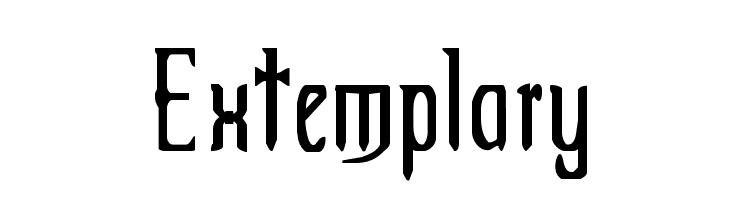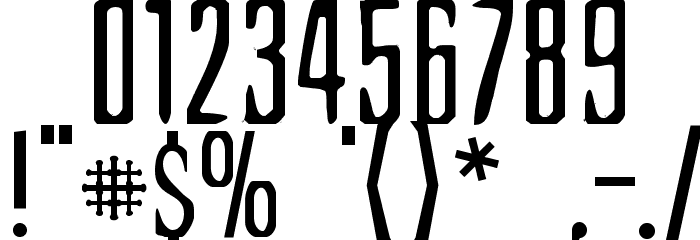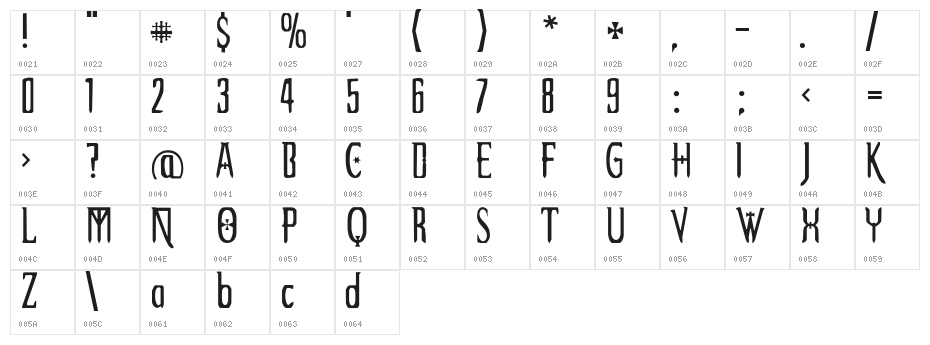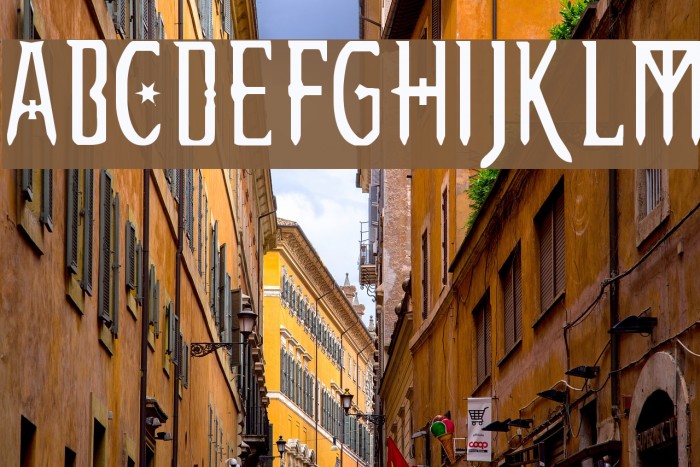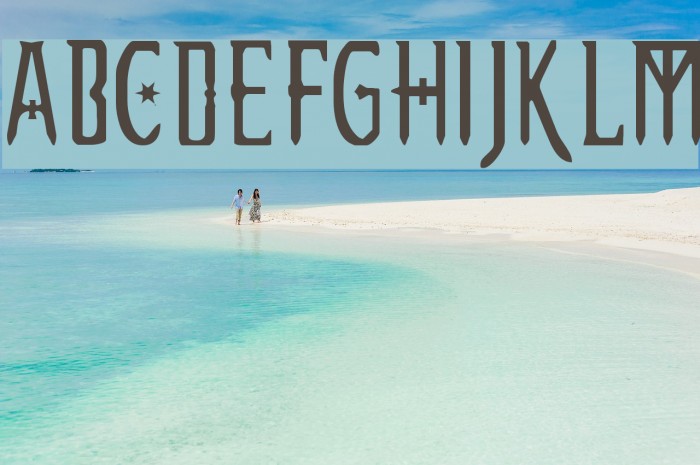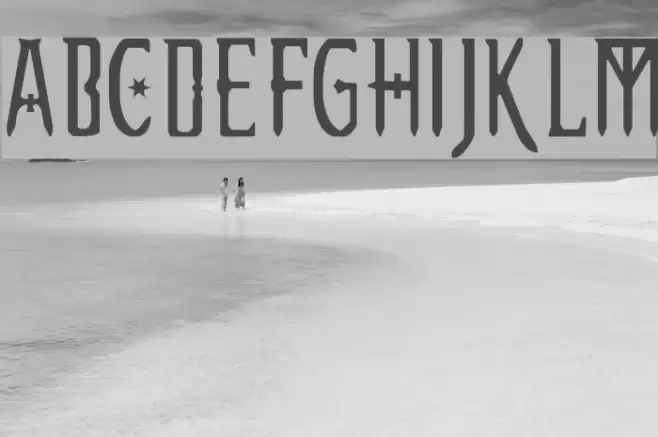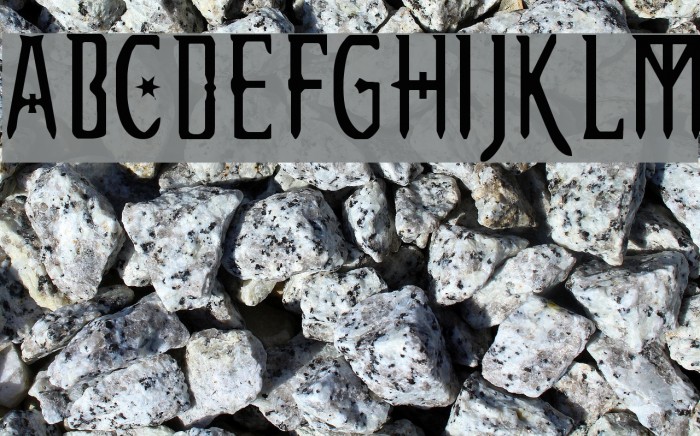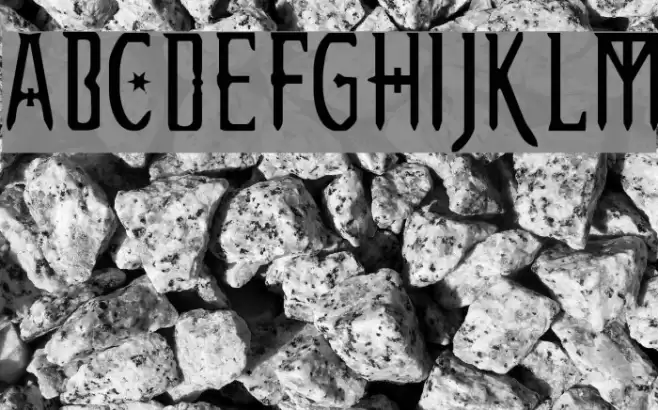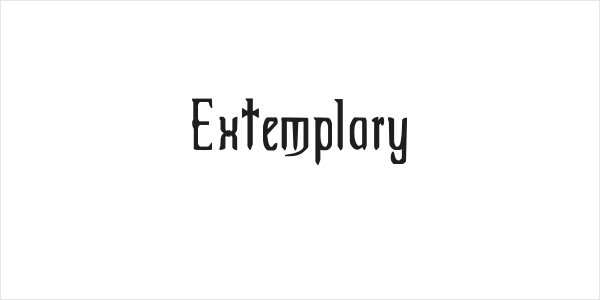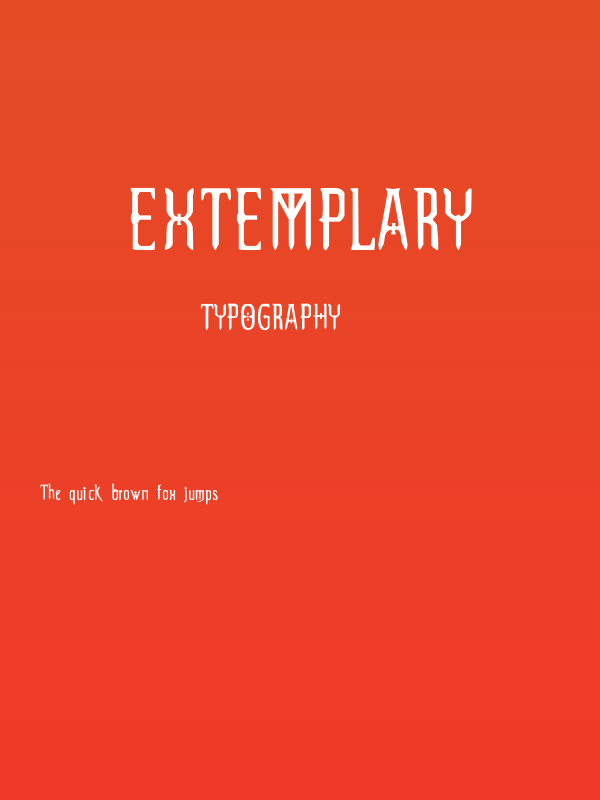
Extemplary Font
| Proyectos propuestos | Ideal for posters, album covers, branding for edgy or alternative products, and any design requiring a bold, artistic statement. |